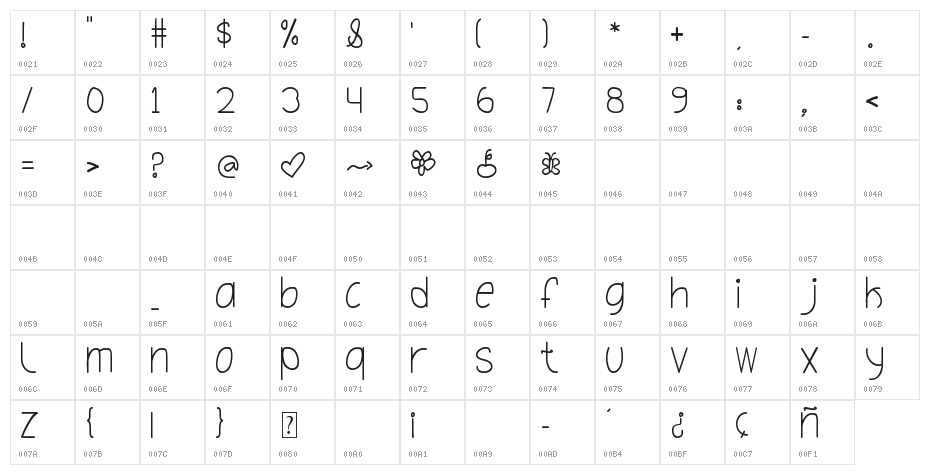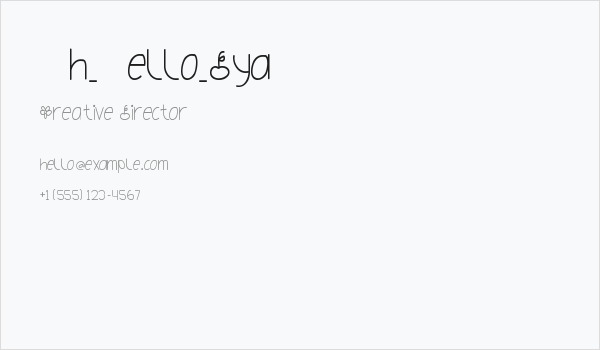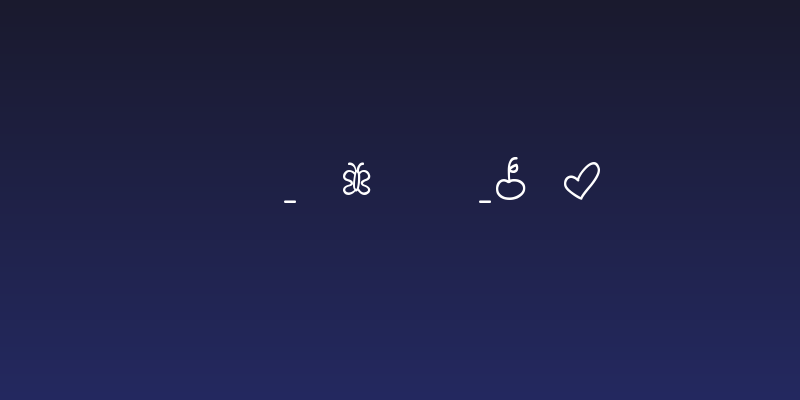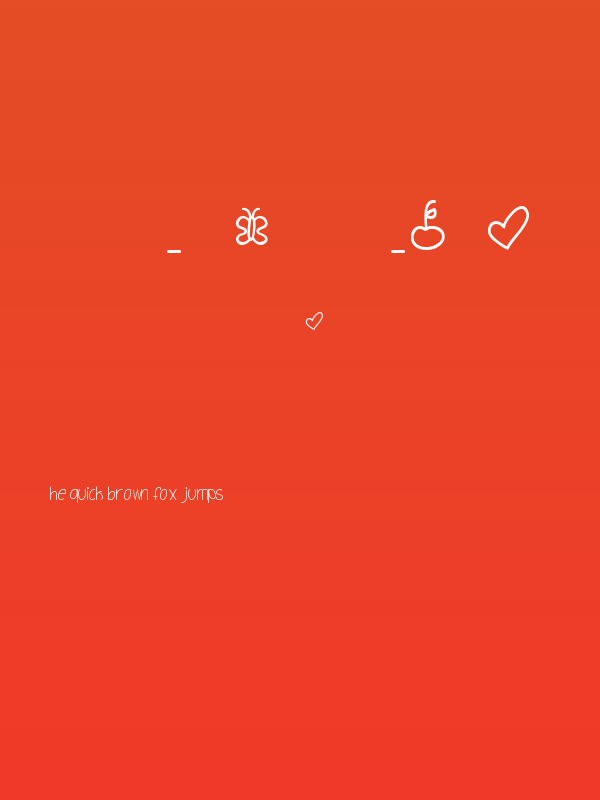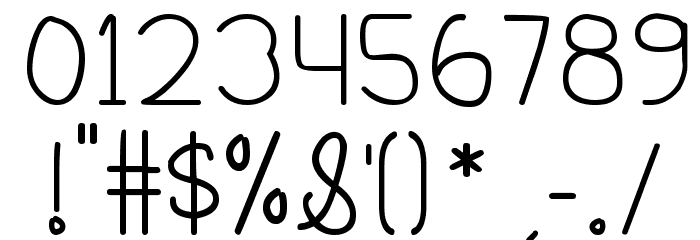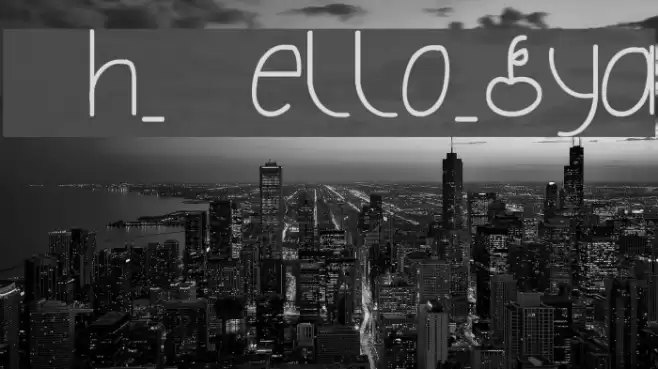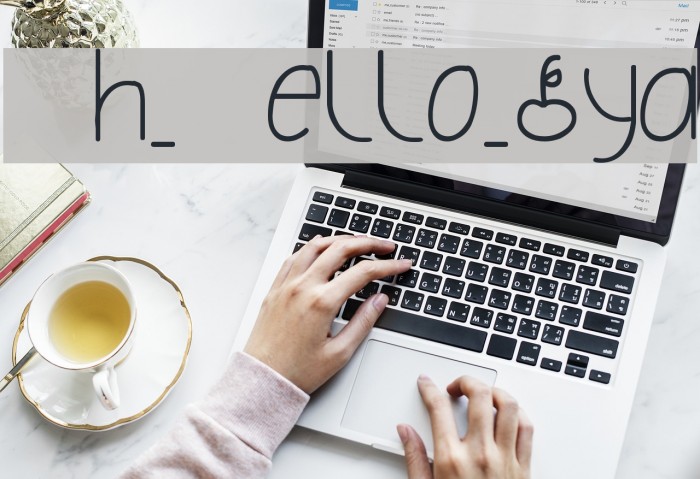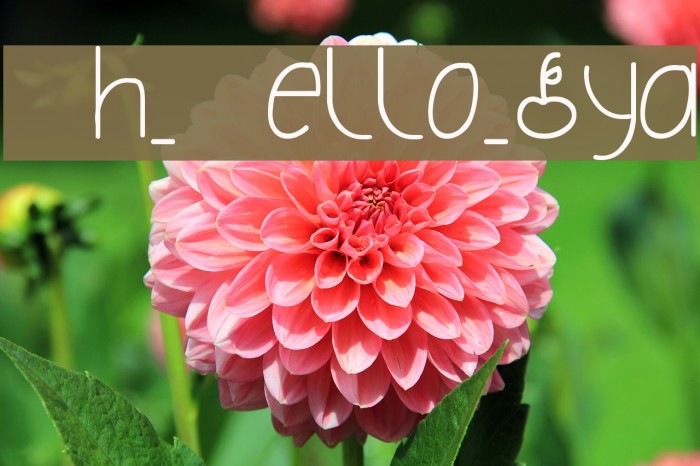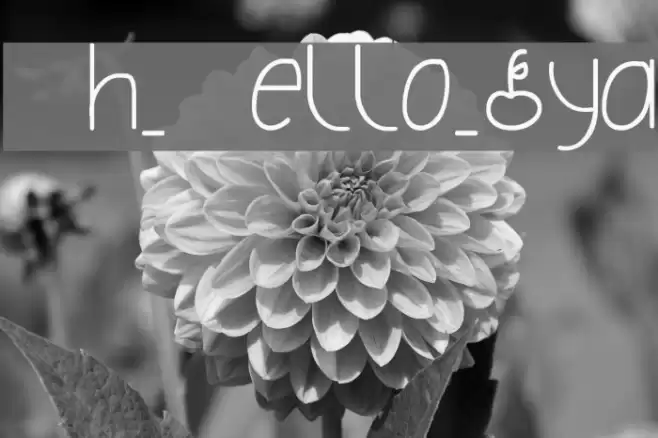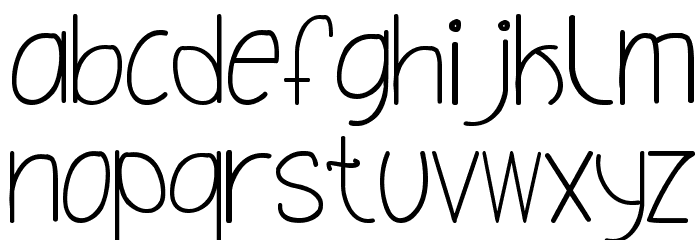
Oh_Hello_Dya Font
✎ Handwritten
| समग्र शैली | Playful, Whimsical |
| उपयोग का मामला | Headlines, Logos, Creative Projects |
| सुझाए गए प्रोजेक्ट | Ideal for children's books, greeting cards, playful branding, and creative social media graphics. |